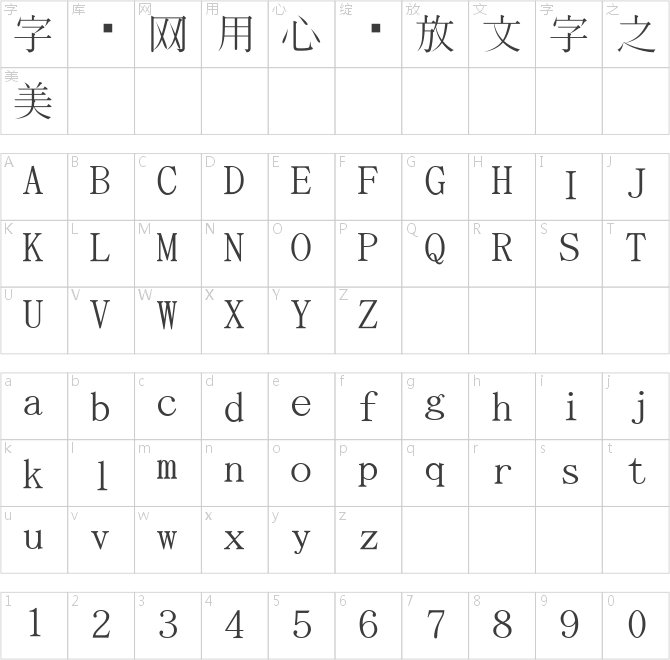
字體名稱: 東風明朝
東風明朝
東風明朝體是日本開源的一款字體,該字體線條較為纖細,字形方正大氣,具有很好的視覺效果 。不過可惜的是,這款字體對簡體中文支持比較差。
東風明朝字體東風明朝字庫是一款讓人賞心悅目、百看不厭的中文字體,適合各類廣告和產品包裝設計應用,字體大小8.55MB,格式為ttf字體,上傳用戶是后天的昨天,作者/版權方為kochi